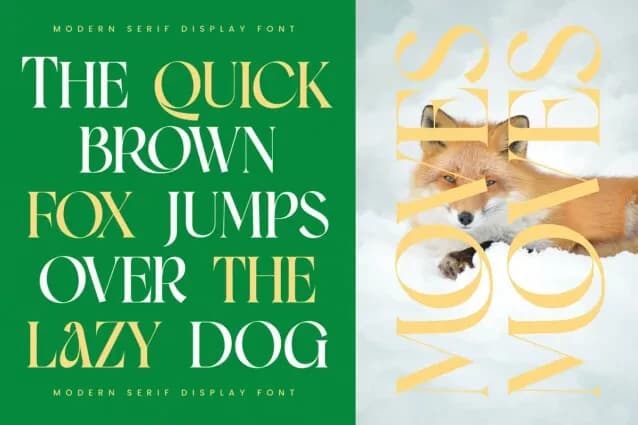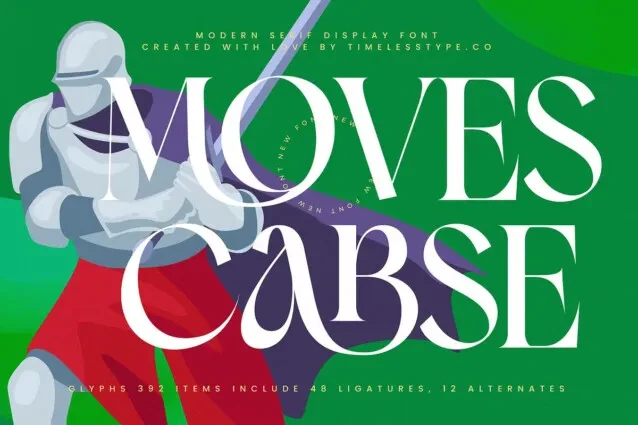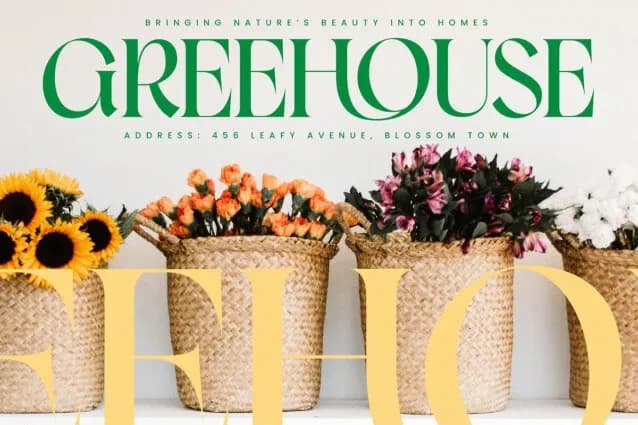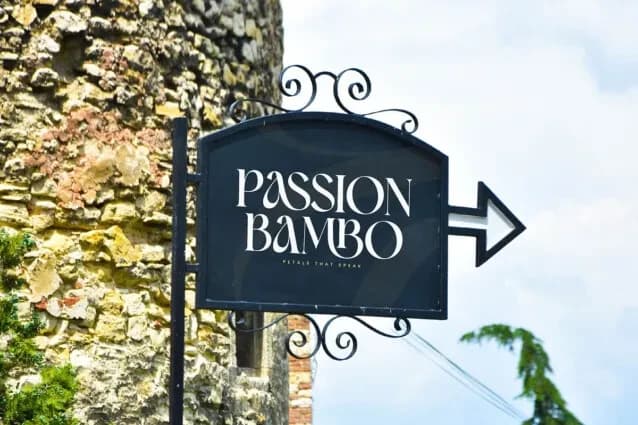
Moves Cabse Font yüksek kontrasta sahip kalın bir serif yazı tipi olup, çok yönlü ve zarif bir tipografi sunar. Logolar, marka kimliği projeleri, ev eşyası tasarımları, ürün ambalajı tasarımları, kupalar, alıntılar, afişler, alışveriş çantaları, tişörtler, kitap kapakları, kartvizitler, davetiyeler, tebrik kartları, etiket, fotoğrafçılık, filigran, özel etkinlikler ve Luxury Serif tadına ihtiyaç duyan diğer tüm lüks ve güzel projeler için de idealdir.
Moves Cabse Font